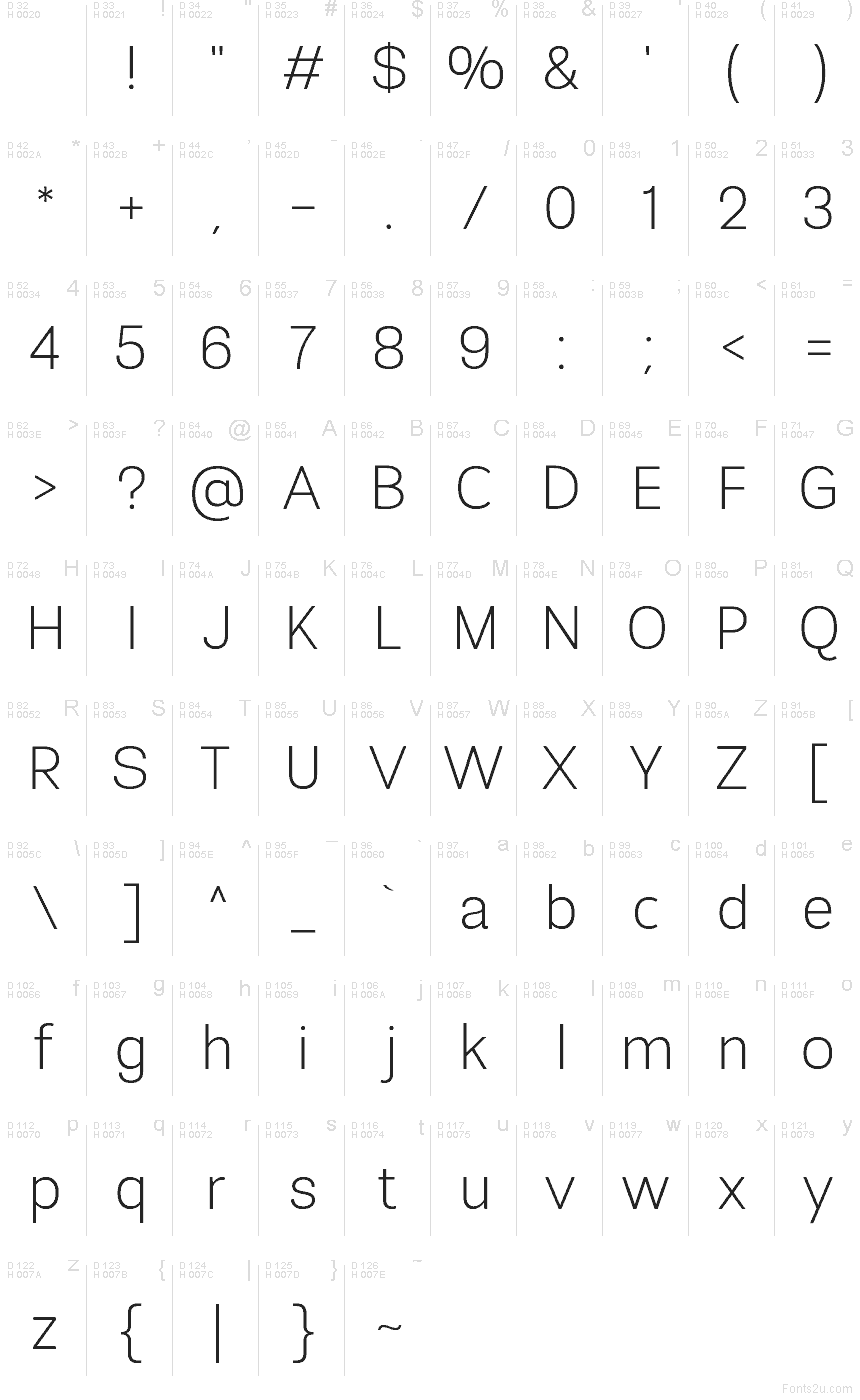
JHC Sineas Extralight da Jehoo Creative é uma fonte gratuita, ultraleve e sem serifa com um toque moderno, elegante e arejado. As letras baseiam-se em traços finíssimos e formas abertas e arredondadas, conferindo à fonte uma sensação de calma e elegância em vez de rigidez, com a suavidade na medida certa nas curvas para evitar um aspeto clínico.
É perfeita para branding de moda, embalagens de cosméticos, cartazes de galerias, lookbooks minimalistas e títulos editoriais onde uma silhueta extremamente fina define o clima. Como fonte gratuita, também é ideal para logótipos refinados, cartões de apresentação e cabeçalhos de sites, especialmente quando se pretende que o espaço e a contenção sejam os protagonistas.